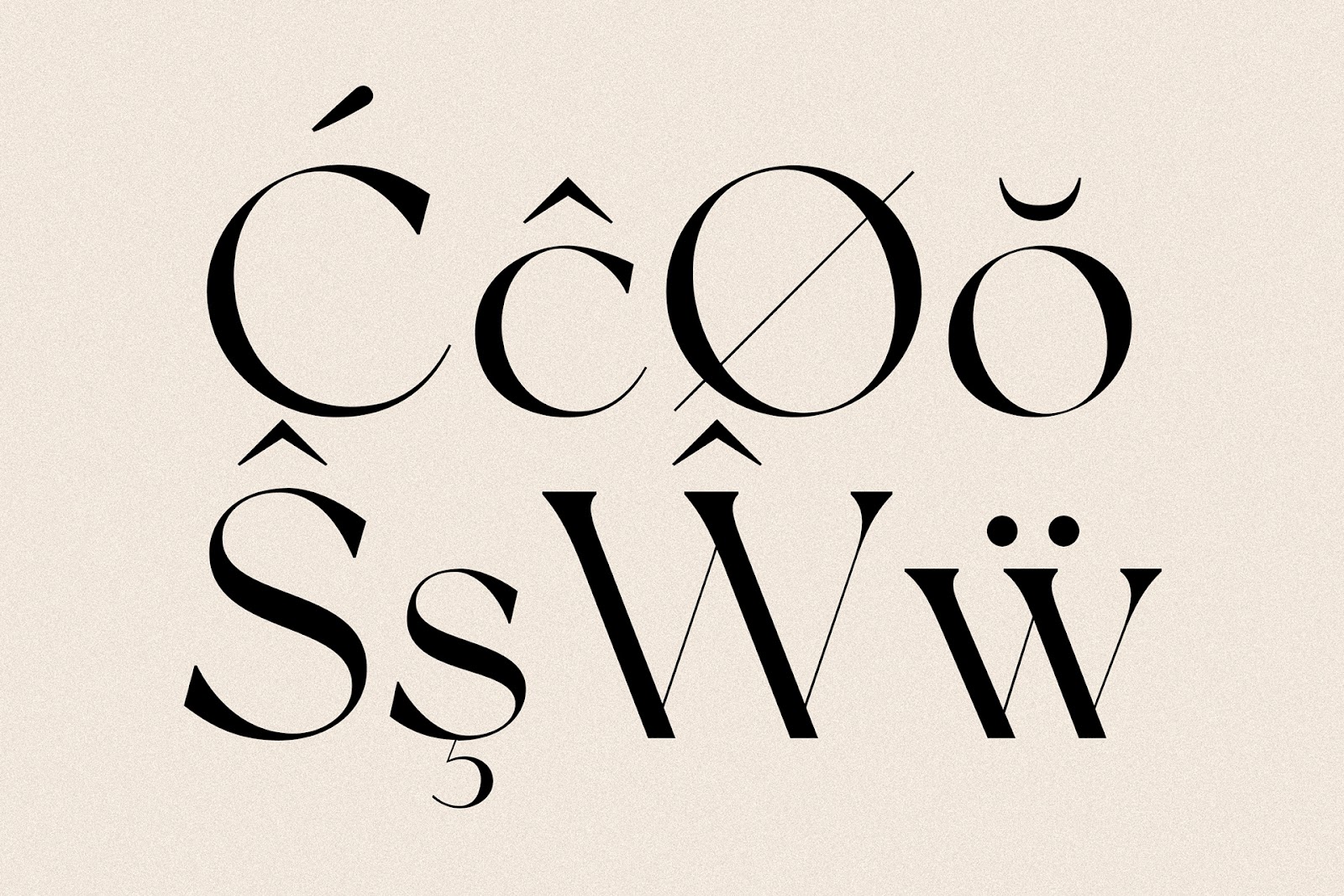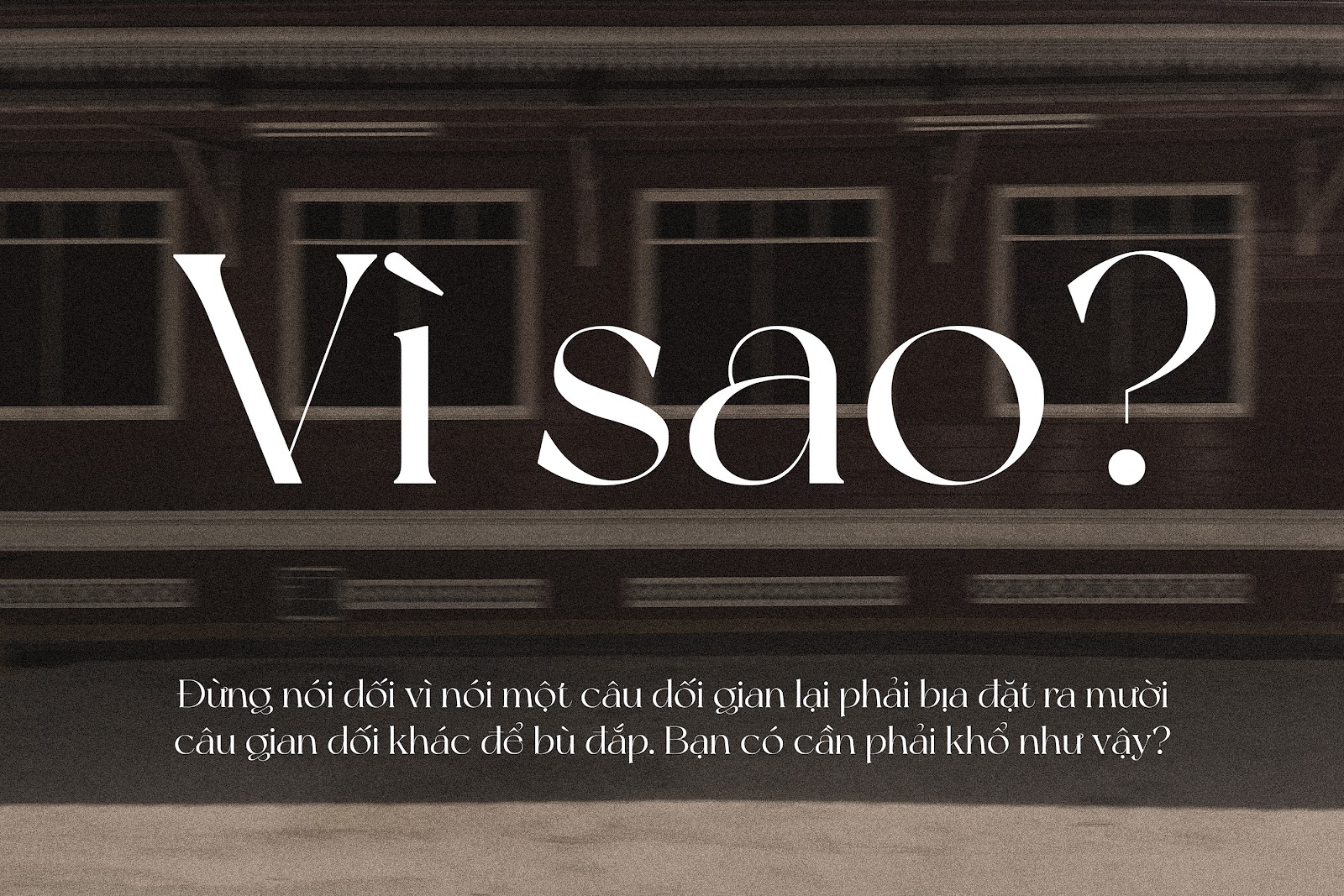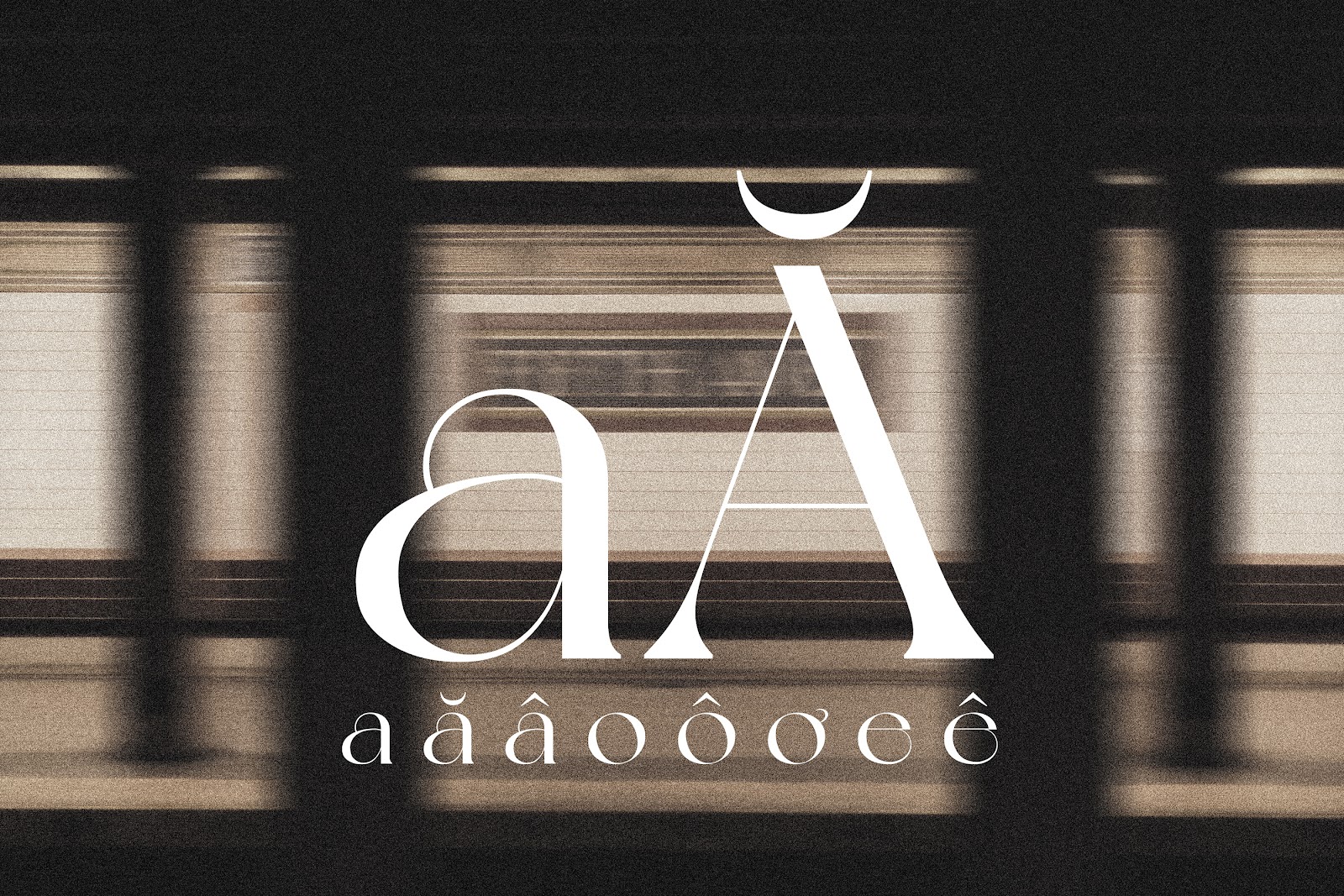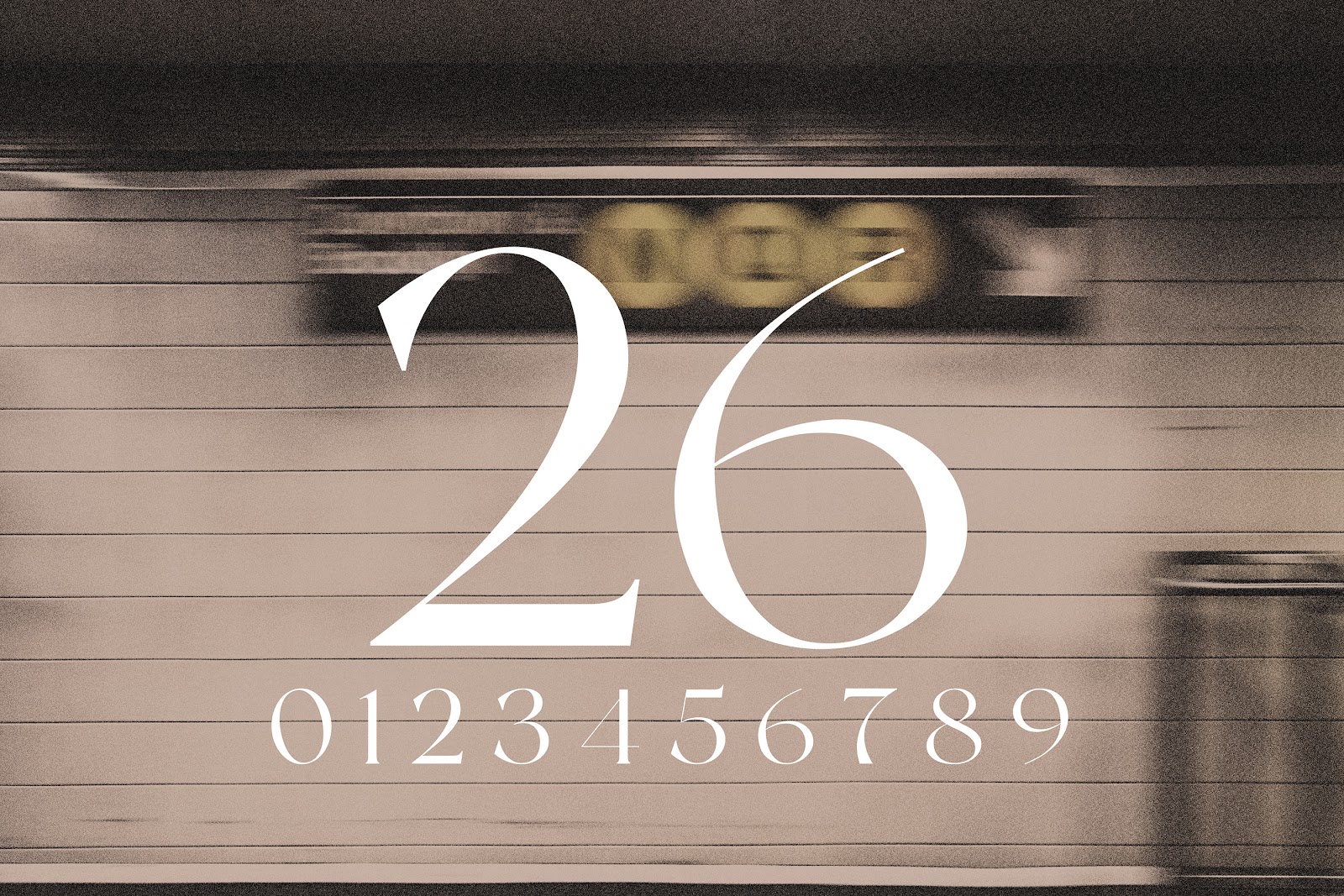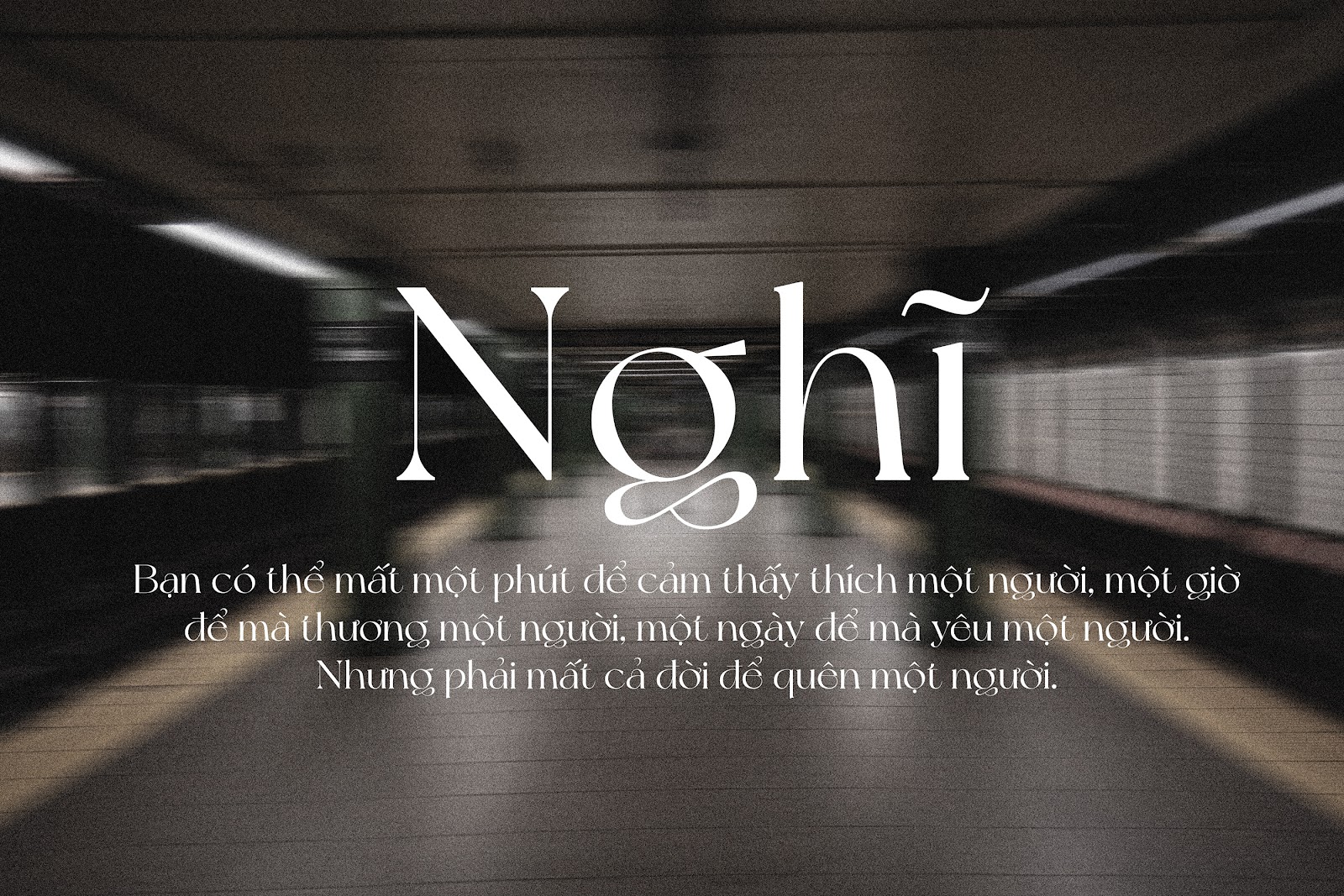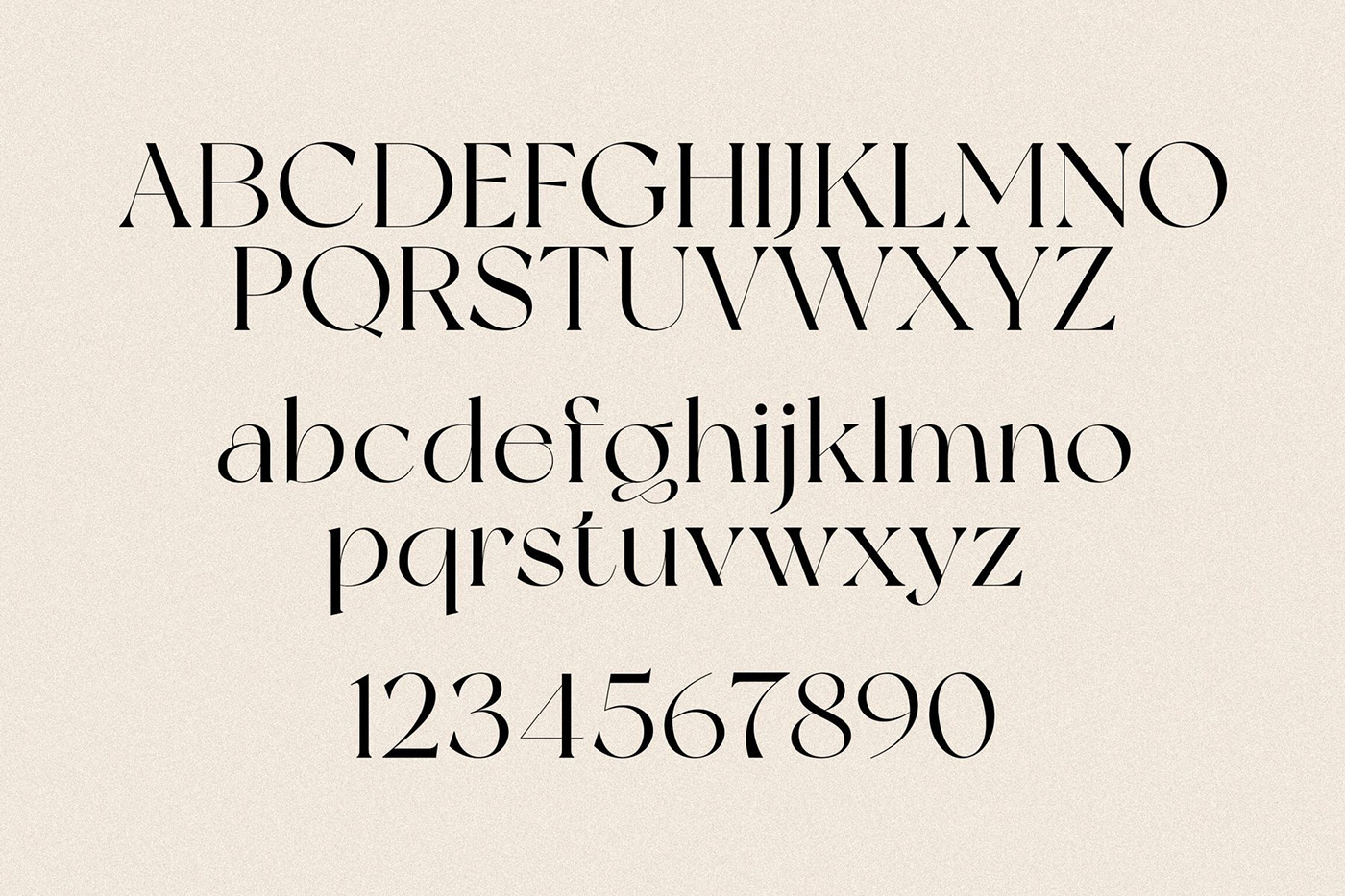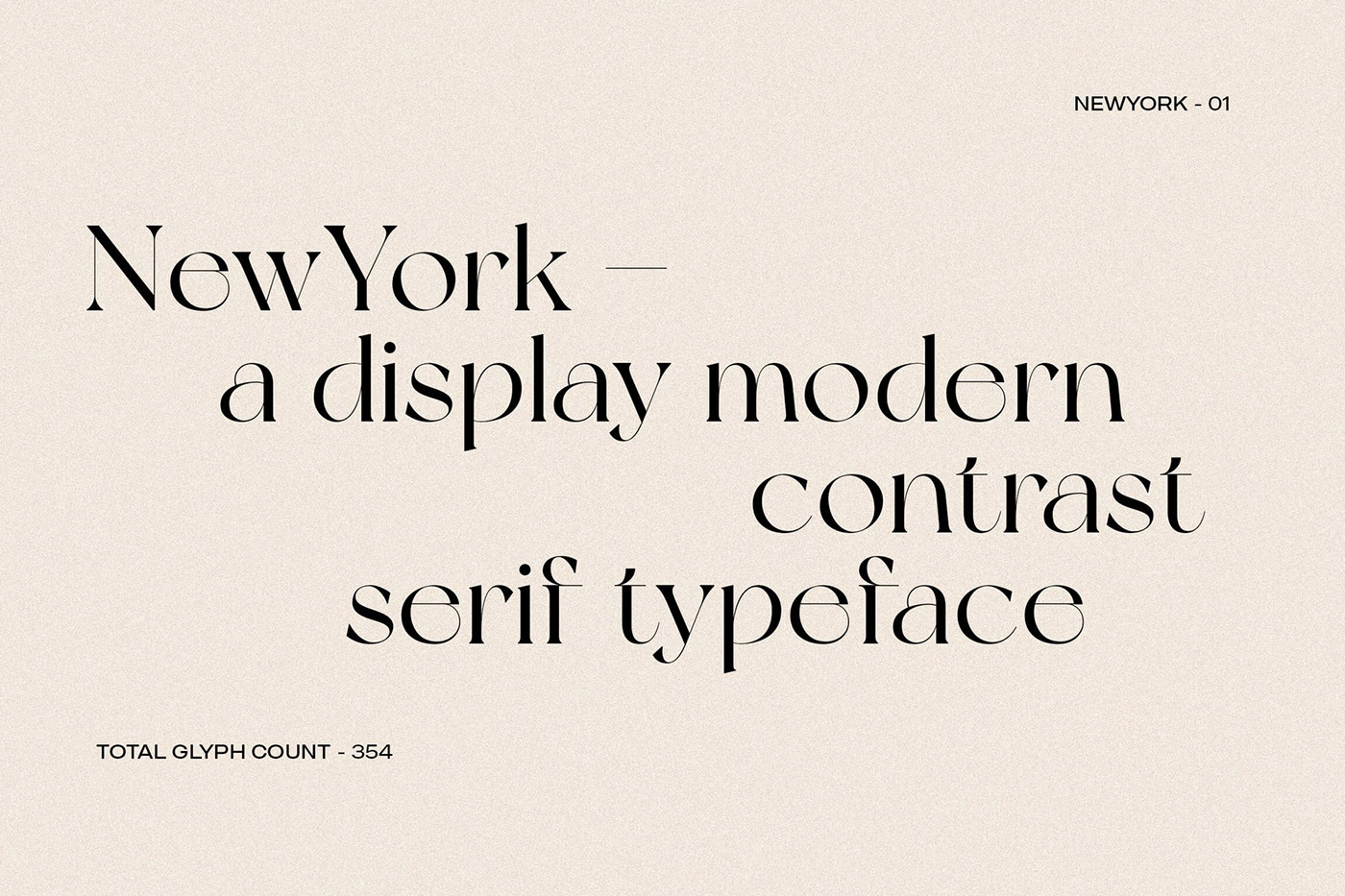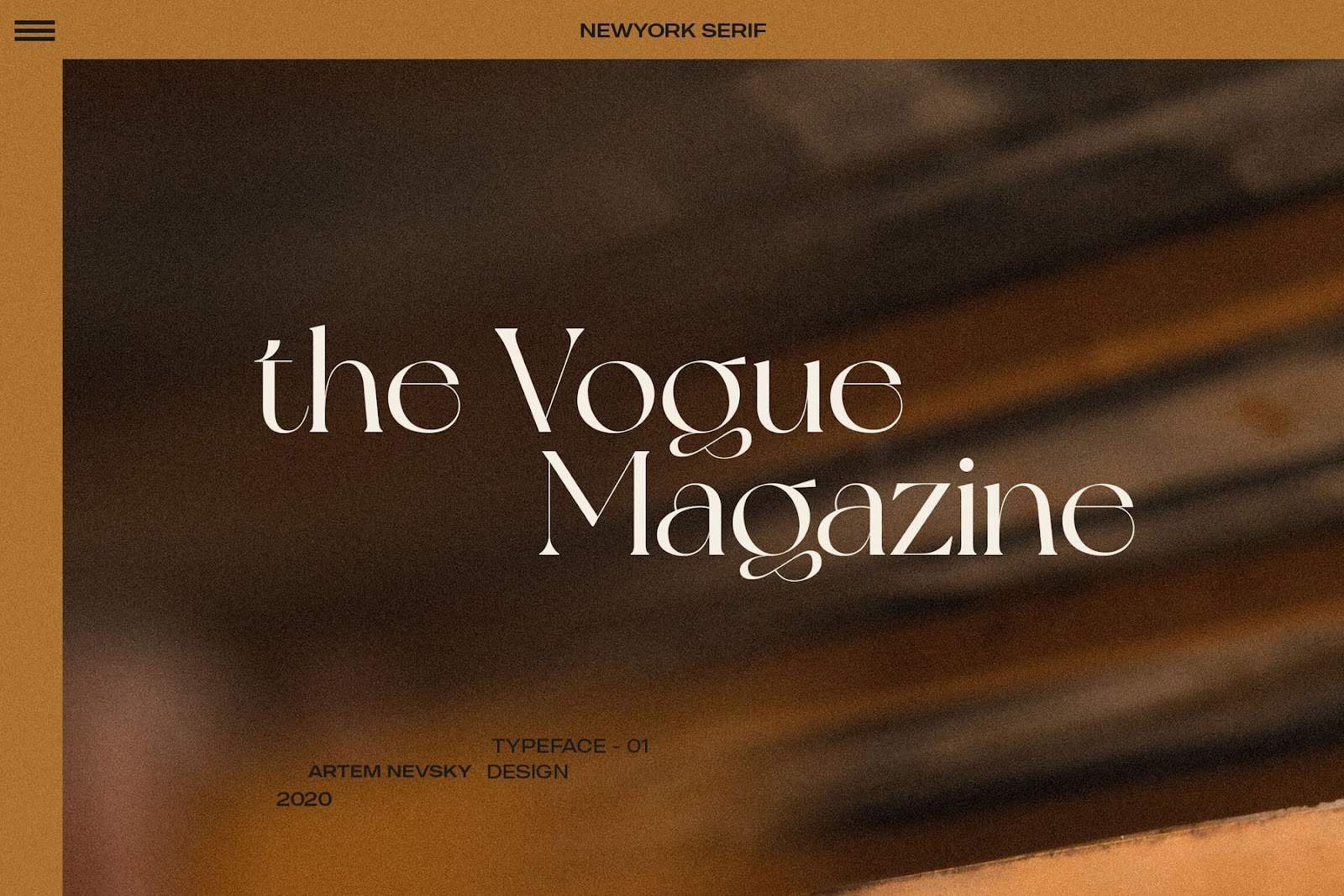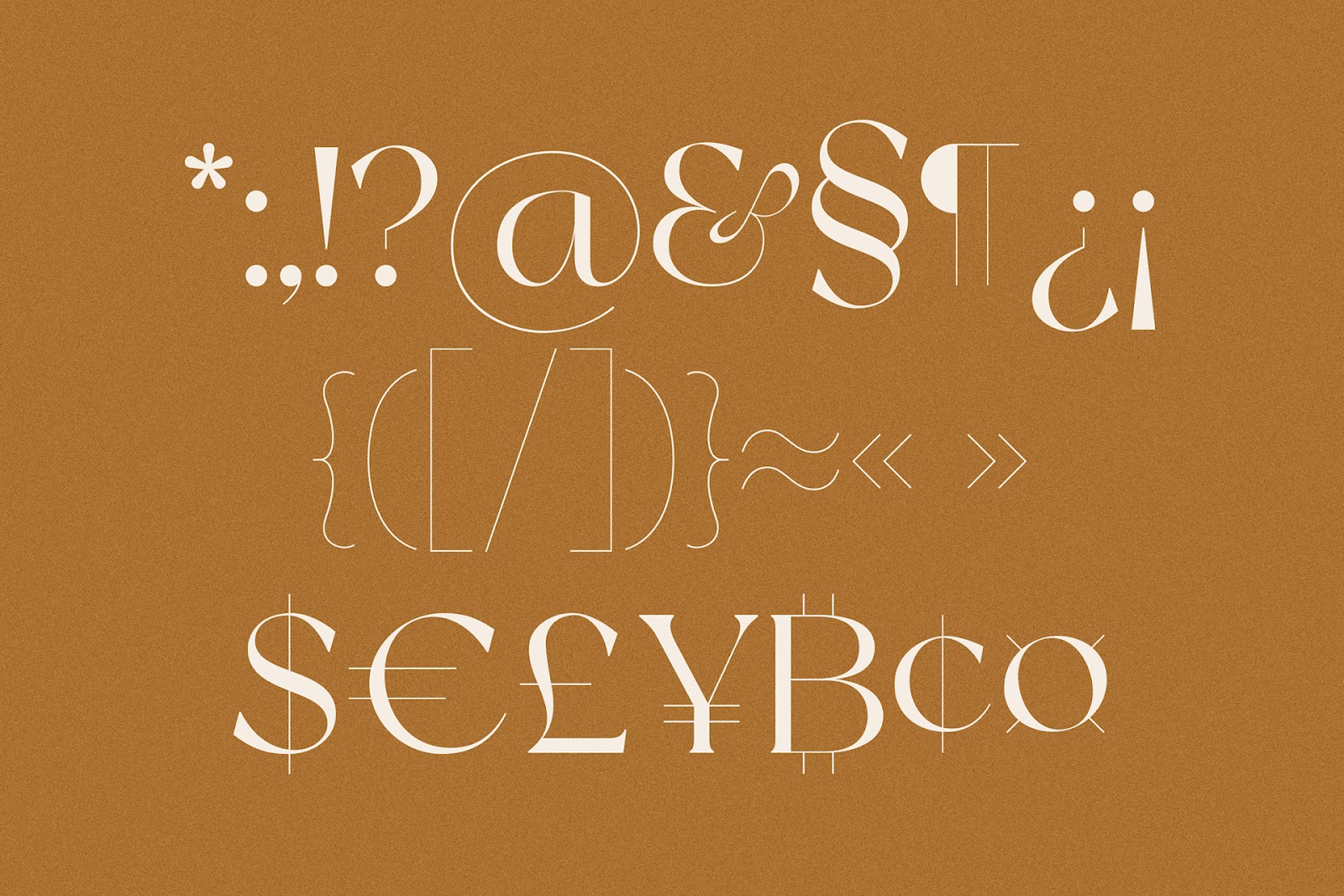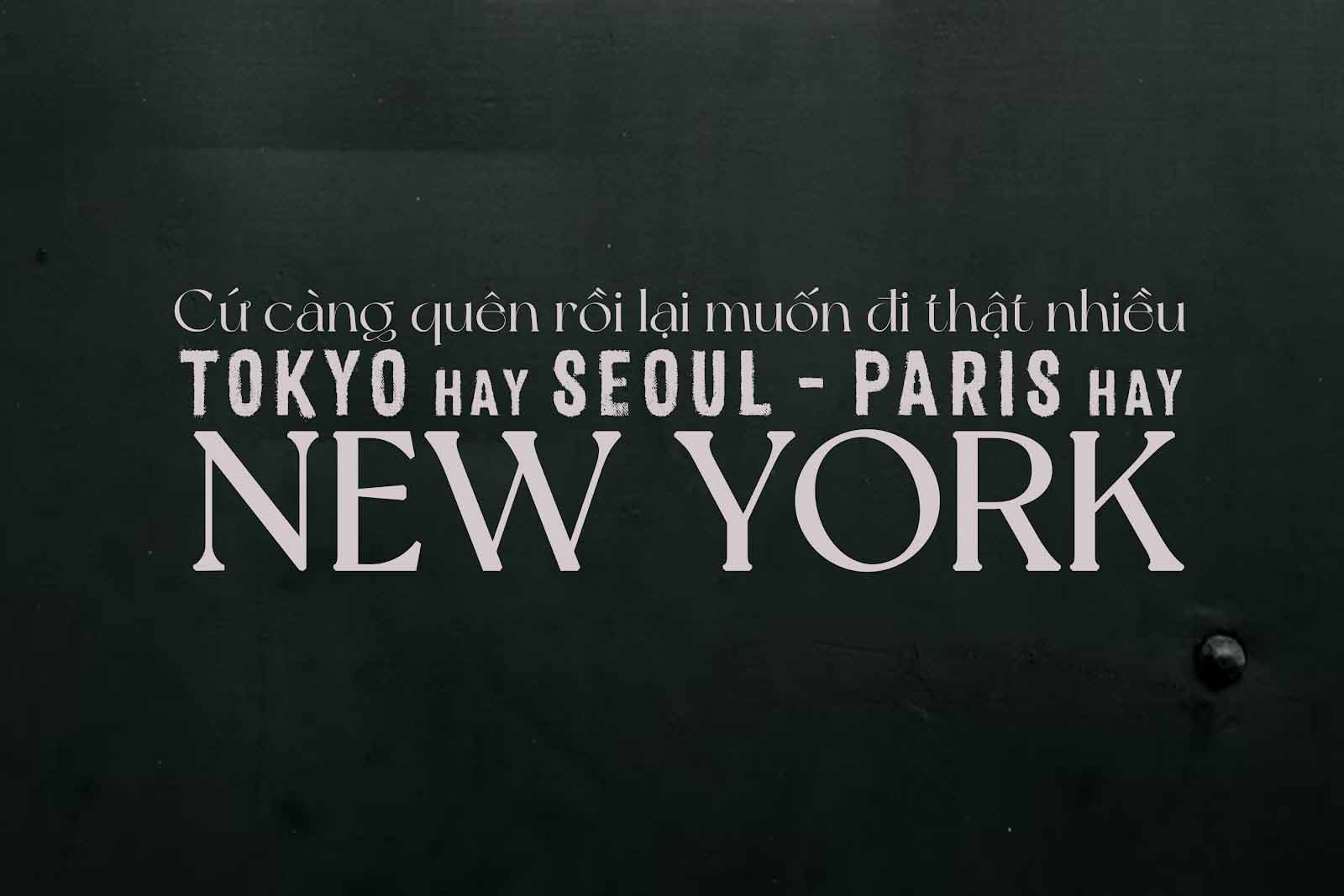
[Serif] Font NewYork Typeface Việt Hóa
NewYork là một phông chữ serif miễn phí tuyệt đẹp được tạo ra bởi Artem Nevsky. Font chữ NewYork Typeface Việt Hóa với trong cách trang nhã hiện đại mang đến những thiết kế ấn tượng và hoàn hảo cho mọi thiết kế của bạn.